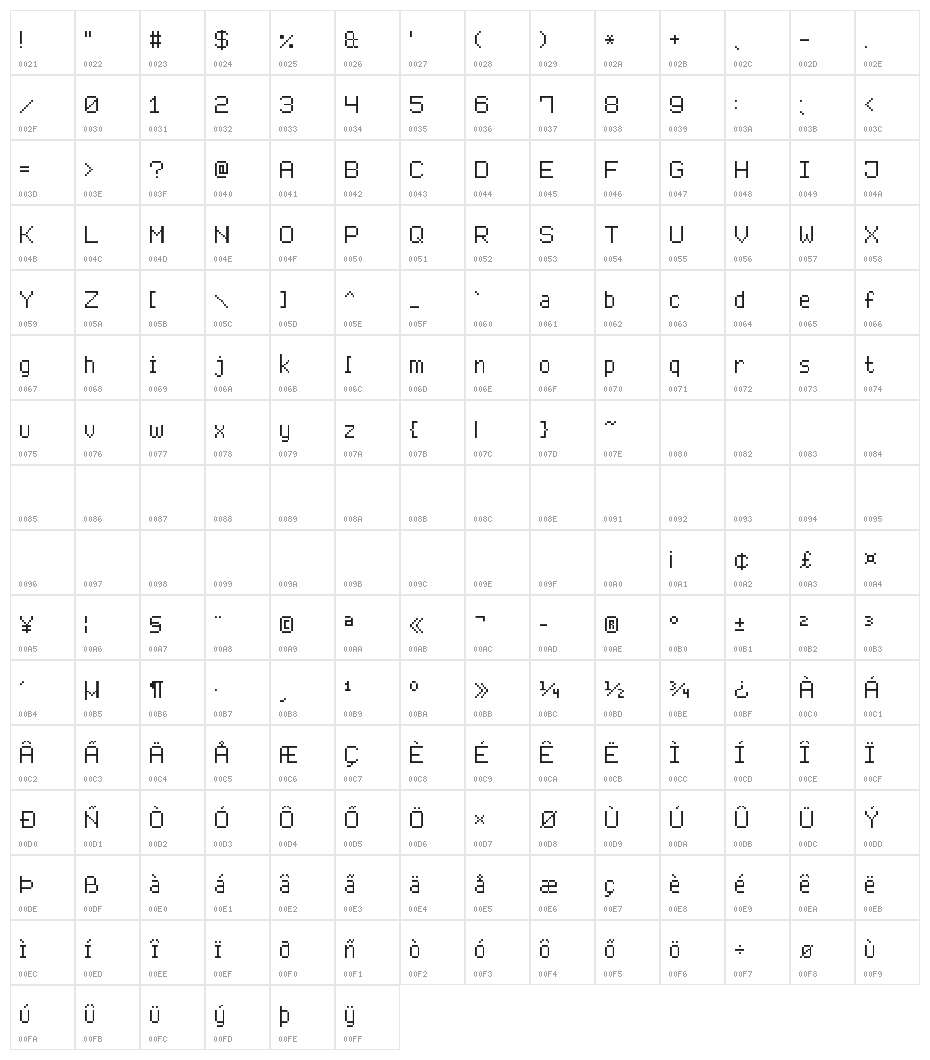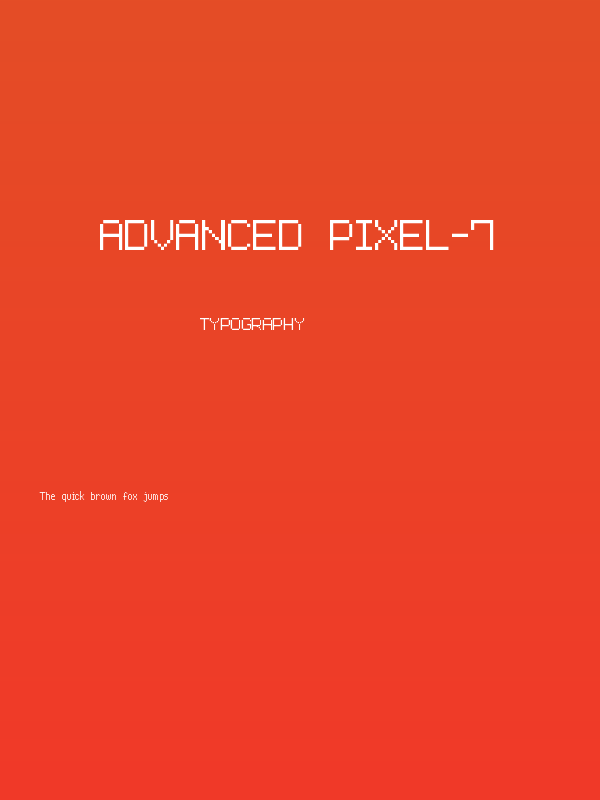
Advanced Pixel-7 Font
✎ Pixel
| Categorie | Pixel |
| Stile generale | Retro, Digital |
| Caso d'uso | Headlines, Logos, Digital Art |
| Progetti proposti | Ideal for video game design, retro-themed posters, digital art projects, and tech-related branding. |